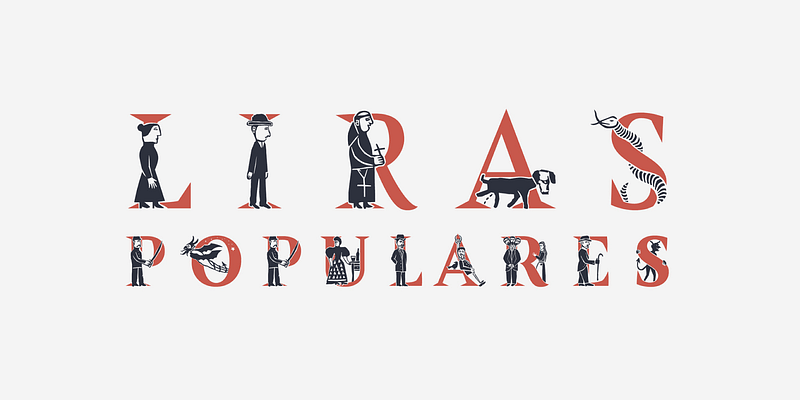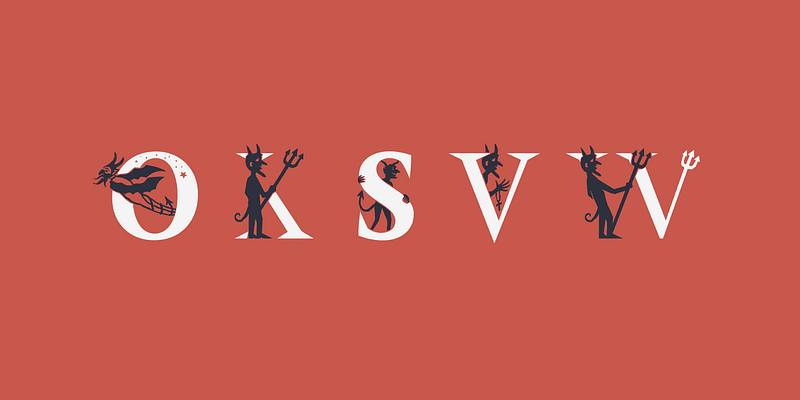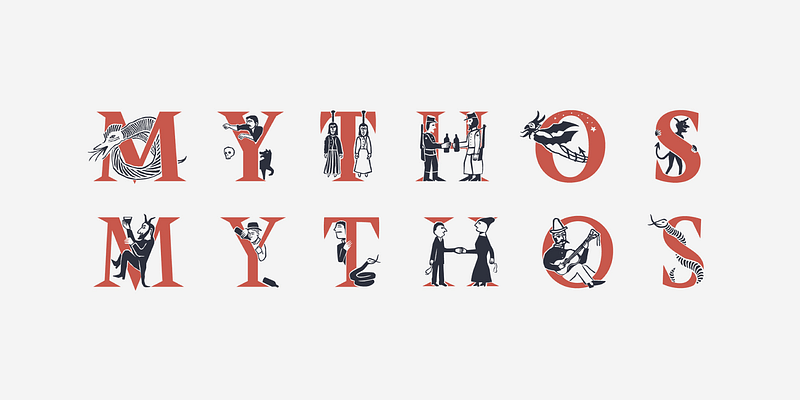
Inspiriert von einheimischen Nachrichtenblättern aus dem Chile des 19. Jahrhunderts, ist Amster Versal Iluminada eine Reihe sorgfältig beleuchteter, vielschichtiger Kapitelle, die Persönlichkeiten aus natürlichen und übernatürlichen Geschichten einfangen: Tiere und Bauern, Priester und Teufel, Bürger und Betrunkene, Opfer und Kriminelle. Ideal, um poetische Töne zu erzeugen und die Fantasie der Leser anzuregen.